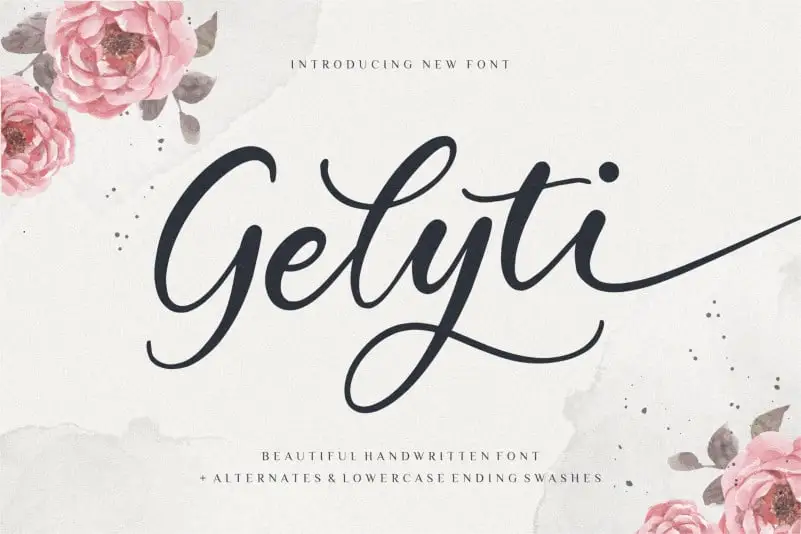
Gelyti Handwritten Font – Fonte Grátis
Gelyti Handwritten Font
A Gelyti é uma fonte escrita à mão que irá adicionar um toque autêntico a seus projetos digitais. Especialmente perfeita para trabalhos como embalagens de produtos, projetos de marca, magazines e redes sociais, também serve bem em ocasiões especiais como casamentos ou quando você deseja expressar mensagens acima de um background. Desenvolvida pelo designer balpirick, a Gelyti oferece uma caligrafia delicada que se adapta perfeitamente para estilos variados e pode ser facilmente integrada em qualquer projeto visual. Com sua natureza elegante e sem compromisso, a Gelyti é o ideal para quem busca um toque humano e único nos seus projetos digitais.